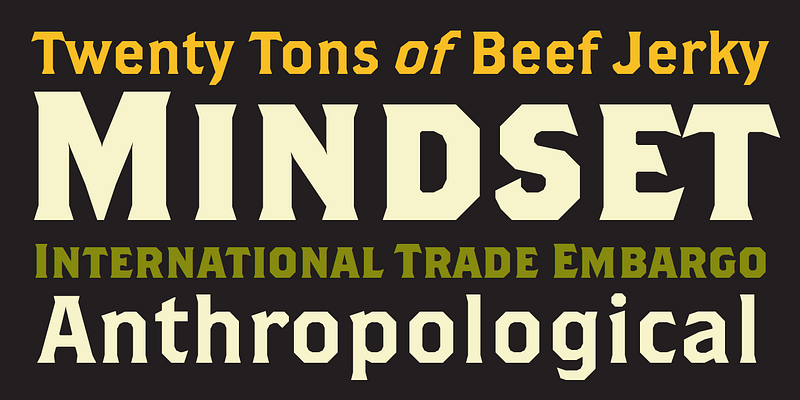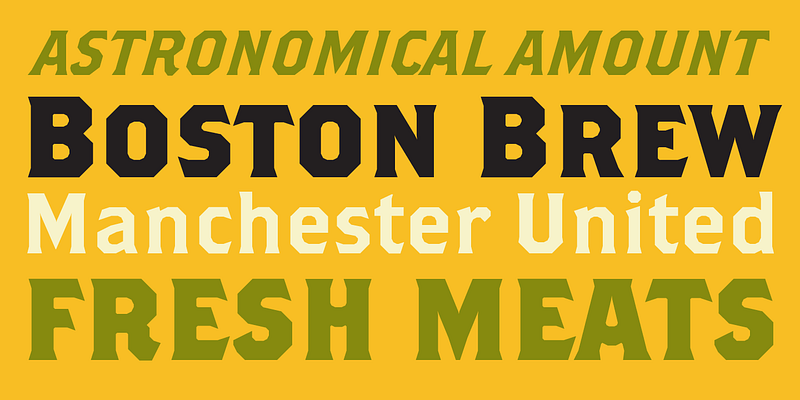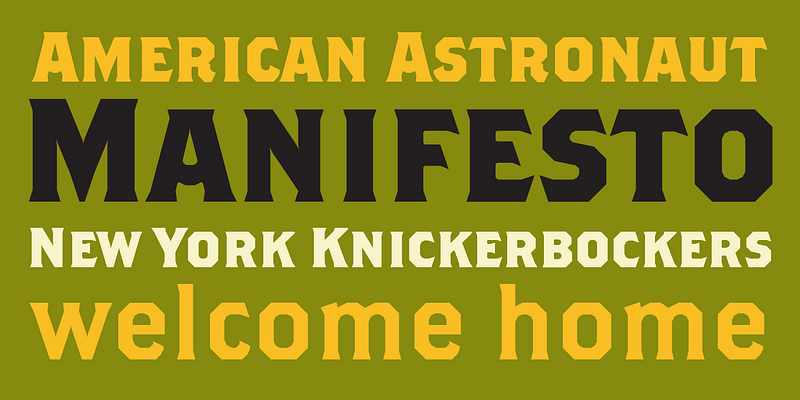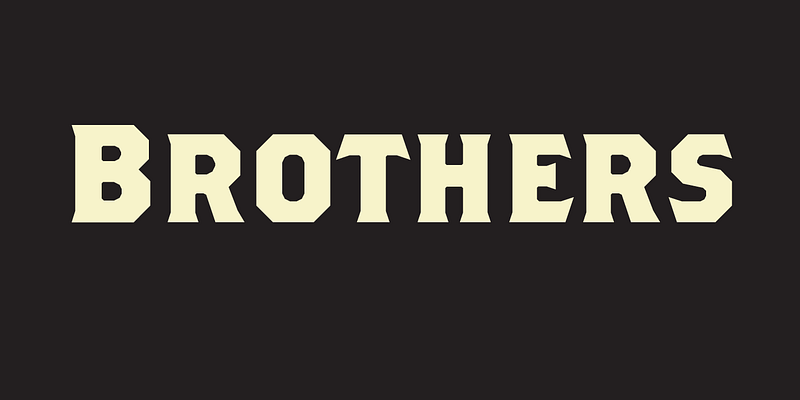
Die Inspiration für Brothers kam von einem leuchtenden chromolithographierten Briefkopf, der um die Jahrhundertwende für die COLE BROTHERS Wandershows entworfen wurde, eine Extravaganz von akrobatischen und zirzensischen Darbietungen, zu denen auch dressierte Pferde mit Reitern ohne Sattel gehörten. Die Kühnheit und der Wagemut der Buchstaben spiegeln die Direktheit und das Draufgängertum der Zirkusartisten wider. Als die Brothers-Schriftenreihe wuchs, schuf Downer mehrere alternative Großbuchstaben für die Bold und entwarf dann eine Regular-Schriftstärke, die stilistisch dazu passte. Als Nächstes folgten ein Kleinbuchstabe für die Regular und ein Satz etwas kleinerer (etwa 90 %) Großbuchstaben für die Bold Caps in voller Größe. Diese haben die gleichen alternativen Formen wie die Begleitschrift. Schließlich wurde eine pseudo-kursive Version der Regular geschaffen. Dabei handelt es sich eher um eine extreme Schrägschrift als um eine echte Kursivschrift (sie hat weniger kursiv inspirierte Formen als die Normalschrift), daher der Name „Super Slant”. Sie verfügt über Alternativen, die denen der Brothers Regular Alternates entsprechen, sowie über ein paar Extras.